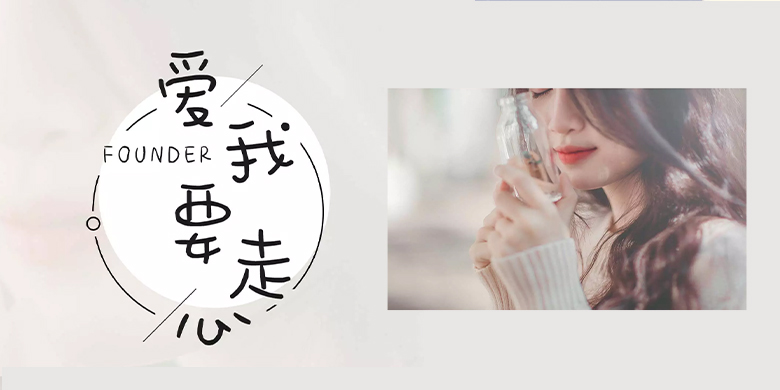
方正手迹-爱我要走心
字体品牌: 方正手迹 设计师:刘晔 字体分类:创意书写 字体属性:精品字 字符集:大陆简体(GB2312-80) 发布时间: 2019
该字体可爱、呆萌,线条圆滑,结构舒展,中宫宽松,重心向中下,是一款比较典型的可爱类字体。适用于少儿类书刊,及现代诗歌、短文的排版以及文化、商业类品牌的广告语设计。